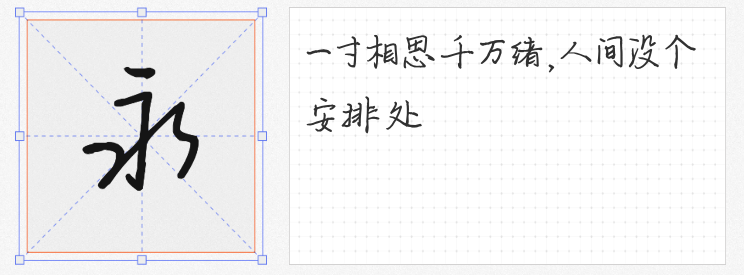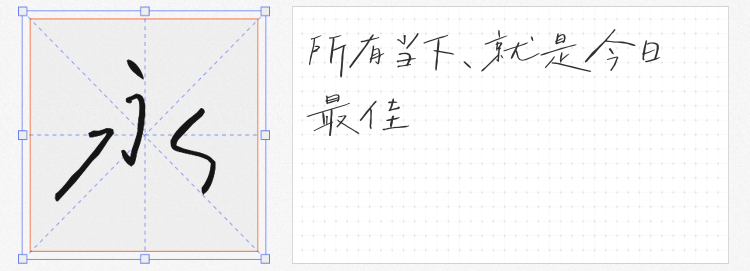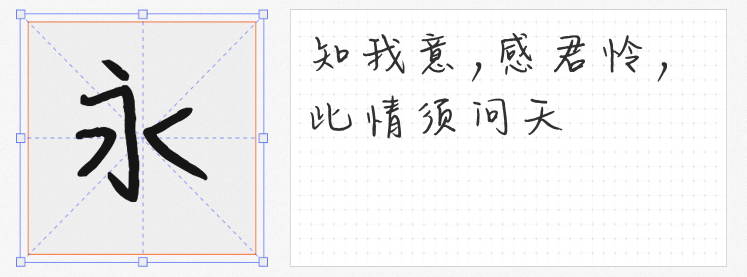
四款宝藏免费手写字体,让你的Vlog文艺感拉满!
在Vlog创作中,一款契合主题的手写字体能瞬间提升画面质感,为内容注入灵魂。今天推荐四款免费商用、风格各异的手写字体,助你轻松打造高级感字幕与封面!
1. 字制区喜脉喜欢体
若想用字体传递自由不羁的文艺气息,这款字体堪称首选。它的笔画灵动飘逸,带有手写时的自然起伏,尤其适合作为封面大标题、歌词字幕或照片排版。例如旅行Vlog中,用“字制区喜脉喜欢体”写下目的地名称,瞬间让画面充满故事感;音乐类内容用它呈现专辑名,艺术氛围直接拉满。推荐场景:自媒体封面、电影海报、杂志标题。
2. 礼品卉自由理想体
这款字体的设计灵感仿佛来自“葛优躺”——横画微弯、竖画慵懒,连方框都化作圆润弧线,像极了周末窝在沙发里的松弛状态。它的不规则笔画能打破刻板印象,为Vlog增添俏皮感。推荐场景:生活记录类字幕、趣味动画标题、手账风格排版,尤其适合搭配治愈系或幽默向内容。
3. 平方洒脱体
笔画粗细适中、线条如行云流水,平方洒脱体的书写感极强,仿佛能看到笔尖在纸上舞动的轨迹。无论是快速切换的短视频字幕,还是产品包装的标题设计,它都能以流畅的视觉效果抓住观众眼球。推荐场景:广告片头、活动海报、动态字幕排版,尤其适合需要强调“速度感”或“活力”的旅行、运动类Vlog。
4. 平方上上谦体
作为硬笔书法字体,平方上上谦体以纤细线条与连贯笔触见长,既有书法的潇洒,又不失现代设计的简洁。它的连笔处理自然流畅,适合需要大量文字排版的场景,如知识分享类Vlog的章节标题或结尾字幕。推荐场景:纪录片字幕、书籍推荐封面、手写风格PPT设计。